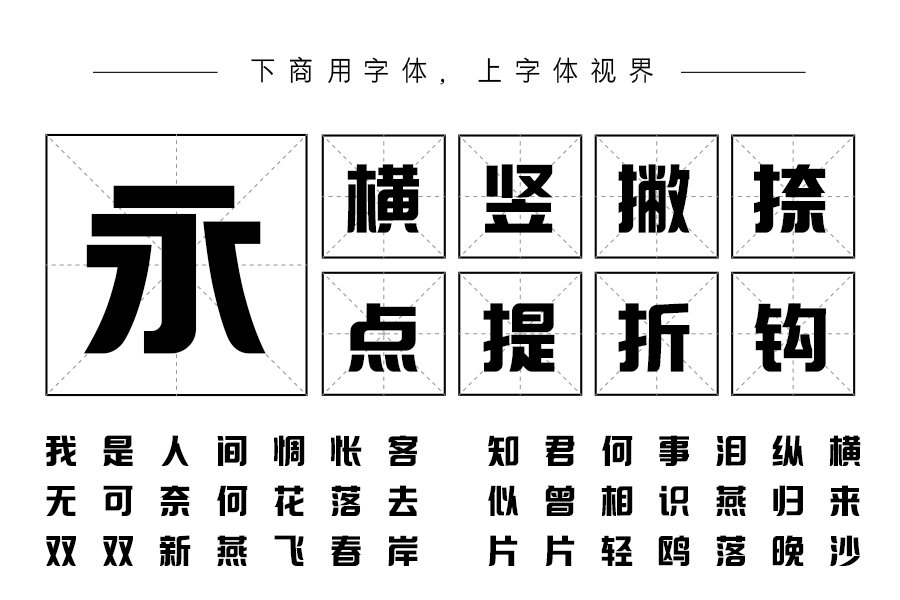
上首标榜体,简体中文约6763字,在字形上属于黑体类型,较宽的笔画赋予了它沉稳的风格,笔画转折处用完美弧线让字体多了一分灵巧,还有特殊的对称处理更加符合中国对称文化美,这样的设计使字体增加了其审美性及文化性,适用于搭配标志、广告标语、商业广告等高端属性。
上首标榜体
字体名称:上首标榜体
上首标榜体